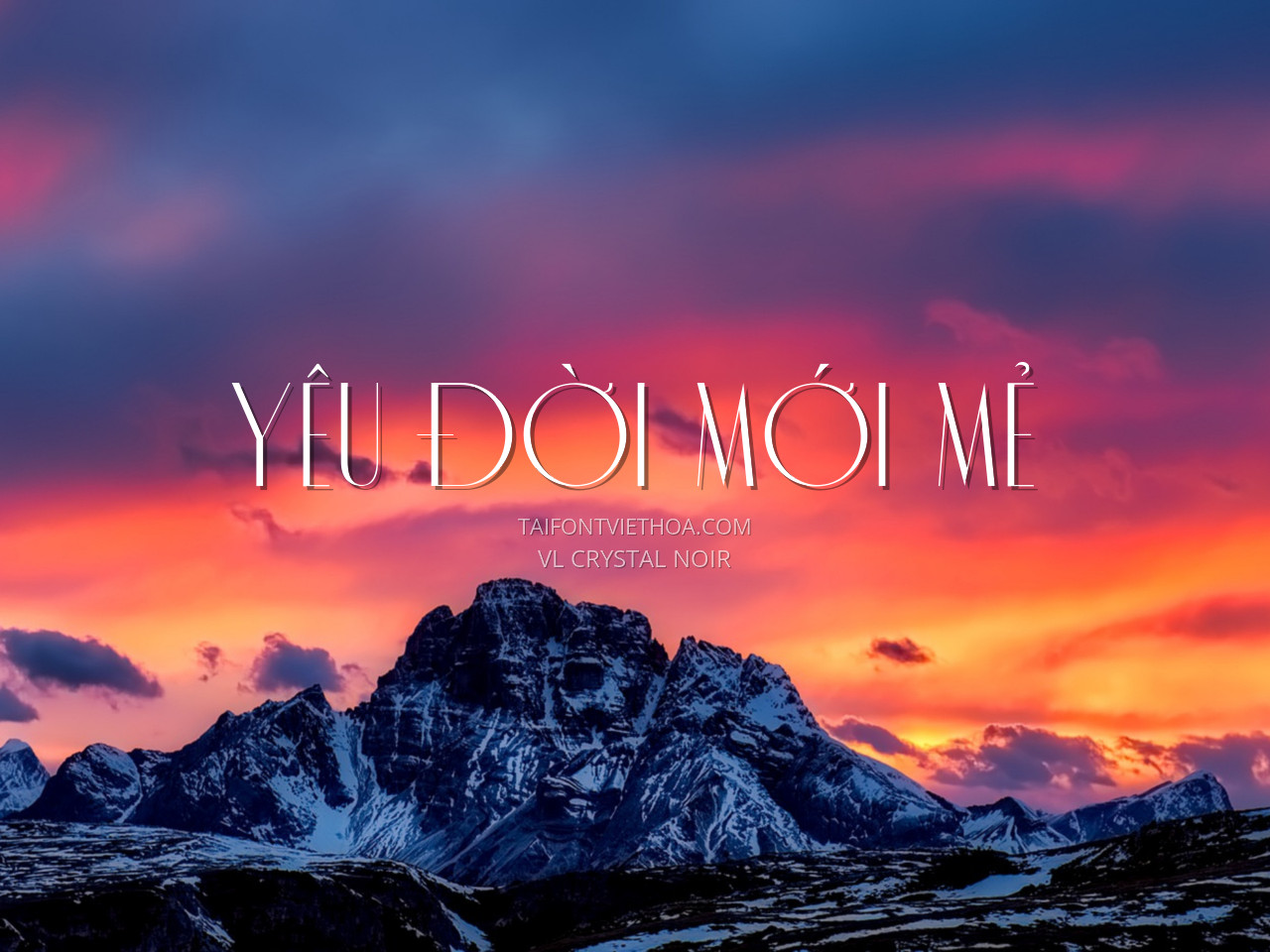
Font việt hóa VL Crystal Noir
Tác giả Font: Calamar Studio
Giới thiệu về font VL Crystal Noir
VL Crystal Noir là một kiểu chữ serif hiện đại, mang vẻ đẹp sang trọng, quý phái với đường nét tinh xảo và giàu tính biểu cảm. Font được thiết kế để tạo nên sự thanh lịch và mạnh mẽ trong các dự án thiết kế cao cấp như thời trang, mỹ phẩm, thương hiệu nghệ thuật. Phiên bản Việt hóa do Font Việt Linh thực hiện, hỗ trợ đầy đủ tiếng Việt với hệ dấu rõ ràng, mượt mà. Ngoài tiếng Việt, font còn tương thích với hơn 60 ngôn ngữ khác thông qua bảng mã Latin mở rộng. VL Crystal Noir đã được taifontviethoa.com chọn lọc, thử nghiệm thực tế và tích hợp vào nhiều dự án truyền thông thương hiệu, in ấn và digital marketing tại Việt Nam.
Đặc điểm thiết kế và ứng dụng của VL Crystal Noir
Font sở hữu đặc trưng của serif hiện đại: phần chân chữ thanh thoát, tỷ lệ chữ hài hòa, kết hợp giữa đường nét mảnh và các chi tiết mạnh mẽ để tạo nên một cảm giác vừa cổ điển, vừa thời thượng. Bộ font phù hợp cho thiết kế tiêu đề, logo, bìa sách, ấn phẩm truyền thông hoặc sản phẩm cao cấp.
VL Crystal Noir lý tưởng cho các ngành như mỹ phẩm, thời trang, thiết kế thương hiệu cao cấp, xuất bản, bất động sản và truyền thông nghệ thuật. Các ứng dụng phổ biến gồm: branding, poster, danh thiếp, website cao cấp, bao bì sang trọng và tài liệu quảng bá sản phẩm nghệ thuật.